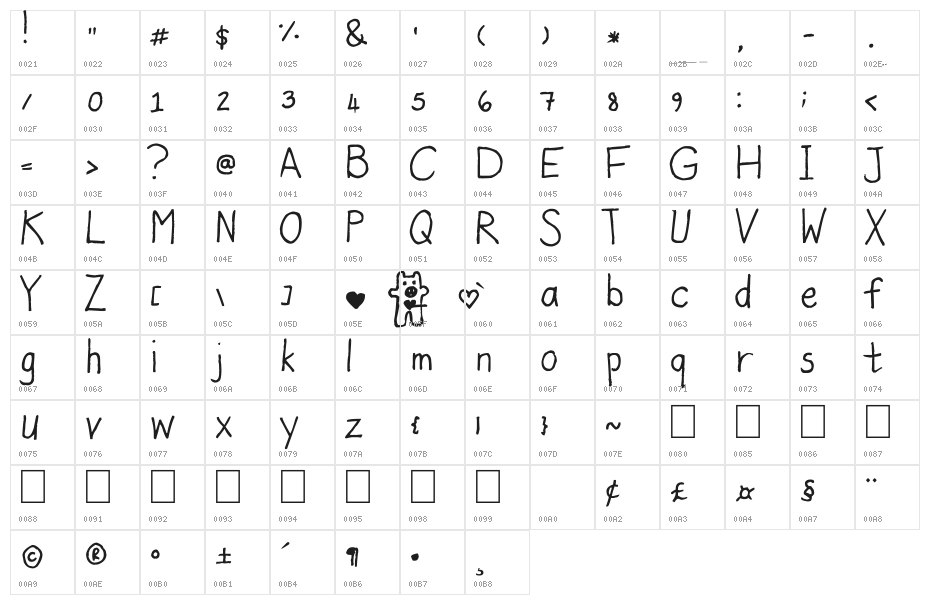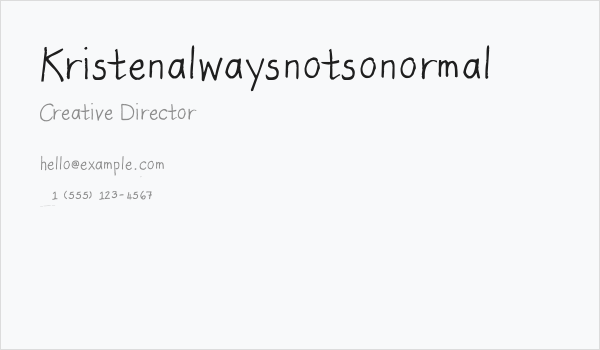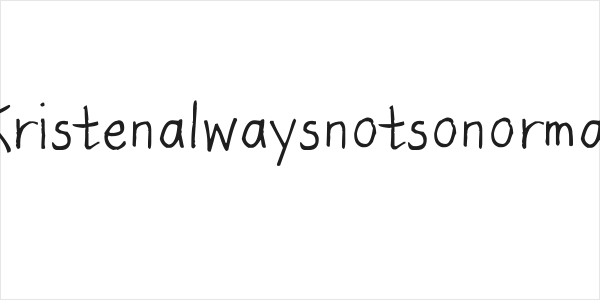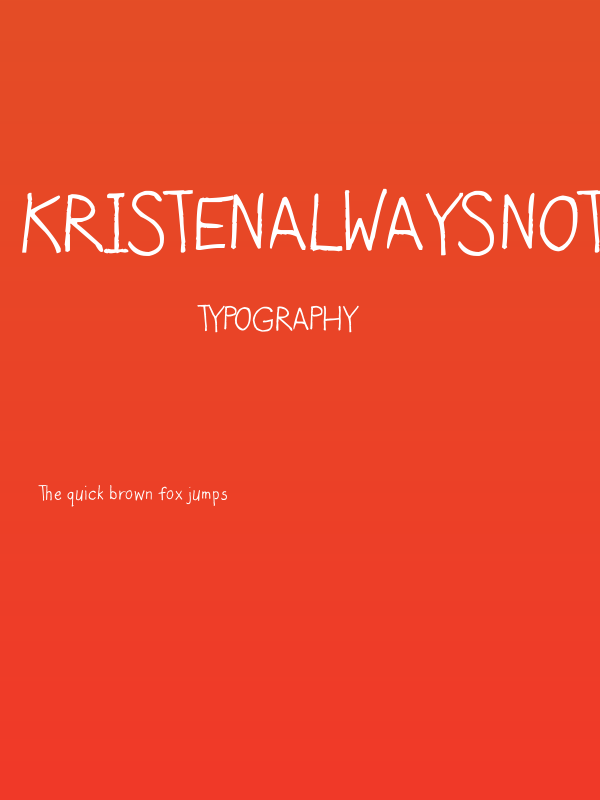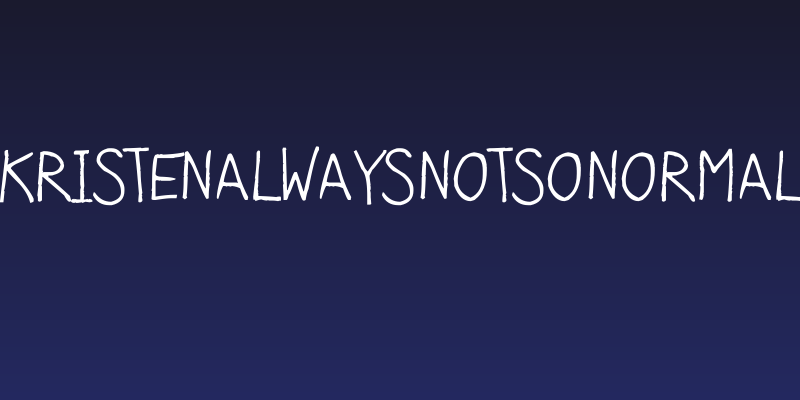
Kristenalwaysnotsonormal Font
| Nome | Kristenalwaysnotsonormal |
| Stile generale | Casual, Playful |
| Caso d'uso | Headlines, Informal text, Creative projects |
| Progetti proposti | Ideal for greeting cards, children's books, personal blogs, and creative branding projects. |